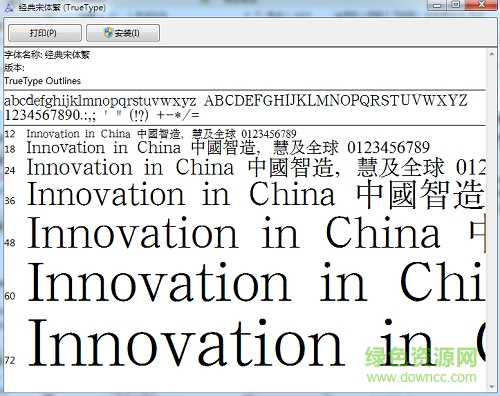
宋體繁體字體是一款字型優(yōu)美的繁體中文字體,秉承原版字體造型秀美適意、剛?cè)岵?jì)的特點(diǎn),字體大小均勻,字庫完整,整體效果相當(dāng)不錯(cuò),安裝方法簡單快捷,感興趣的朋友歡迎下載使用!
宋體,是為適應(yīng)印刷術(shù)而出現(xiàn)的一種漢字字體。筆畫有粗細(xì)變化,而且一般是橫細(xì)豎粗,末端有裝飾部分,點(diǎn)、撇、捺、鉤等筆畫有尖端,屬于襯線字體,常用于書籍、雜志、報(bào)紙印刷的正文排版。